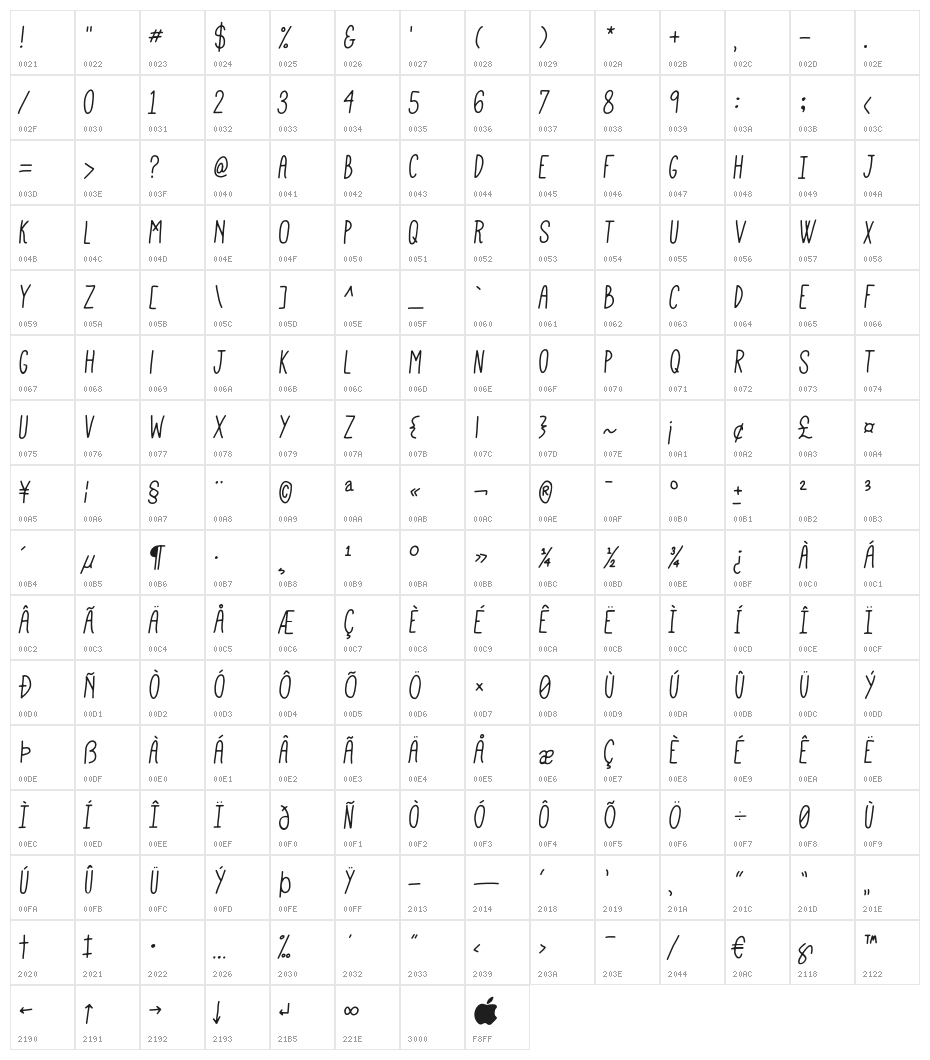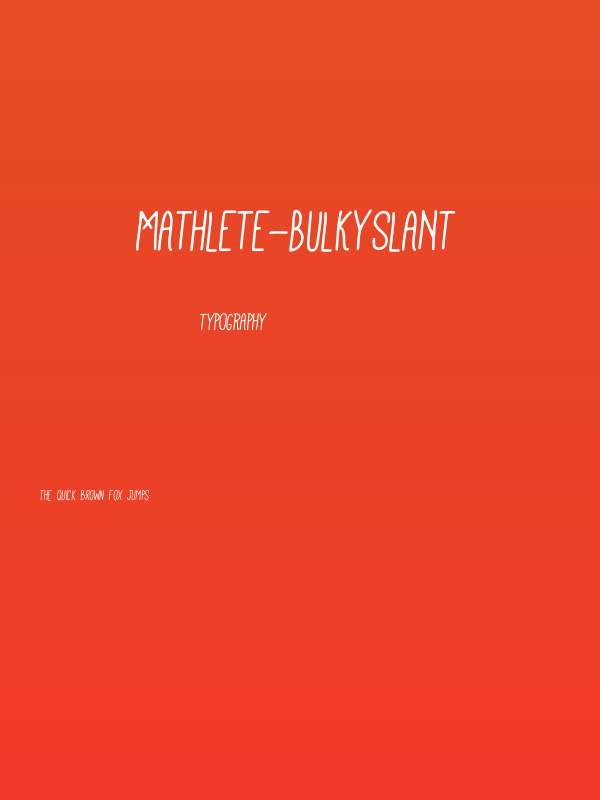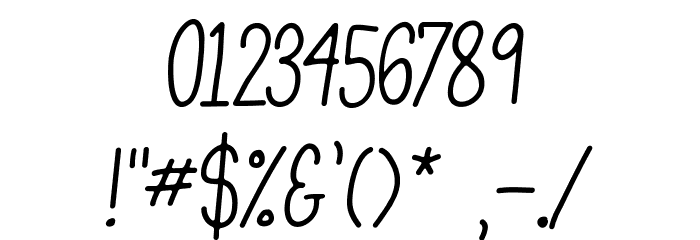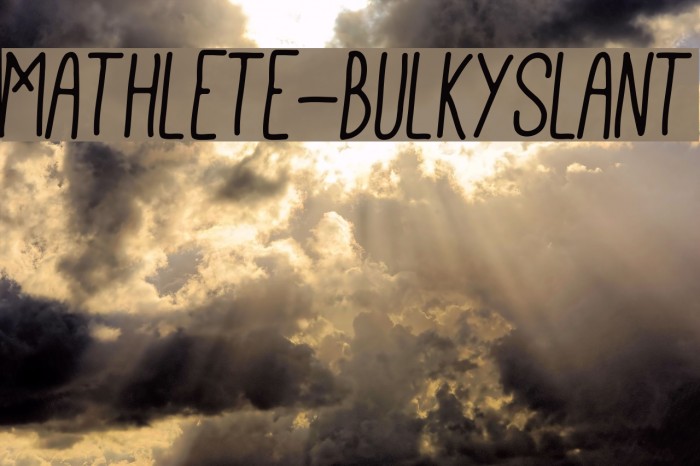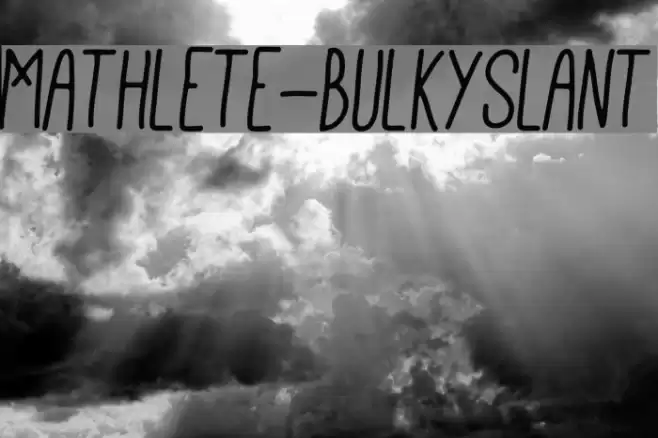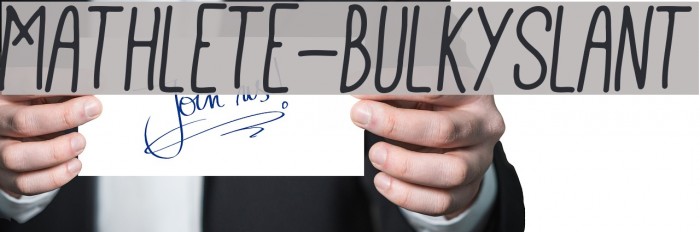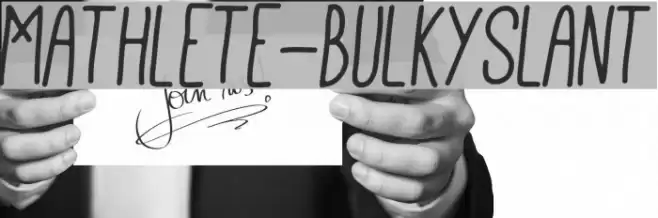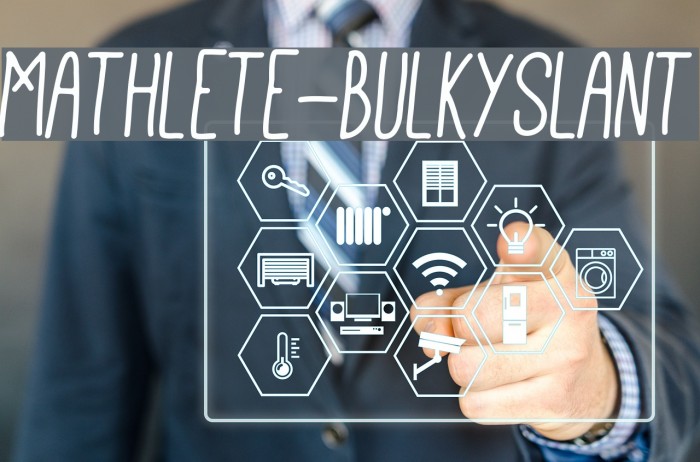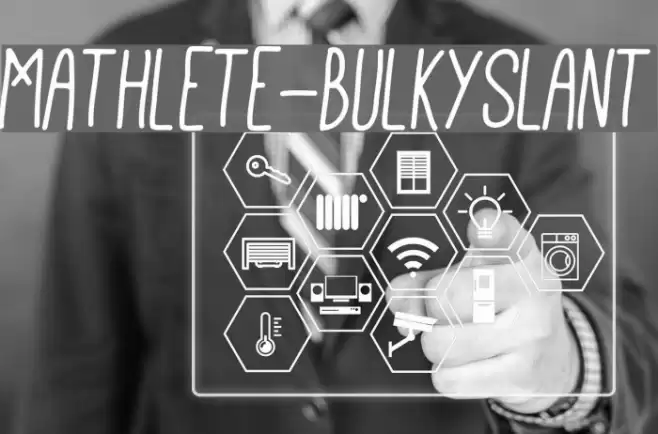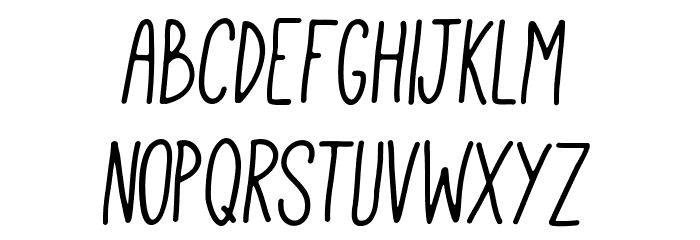
Mathlete-BulkySlant Font
| Общий стиль | Playful, Informal |
| Область применения | Headlines, Logos, Informal Text |
| Рекомендуемые проекты | Ideal for children's books, playful branding, event invitations, and casual social media graphics. |